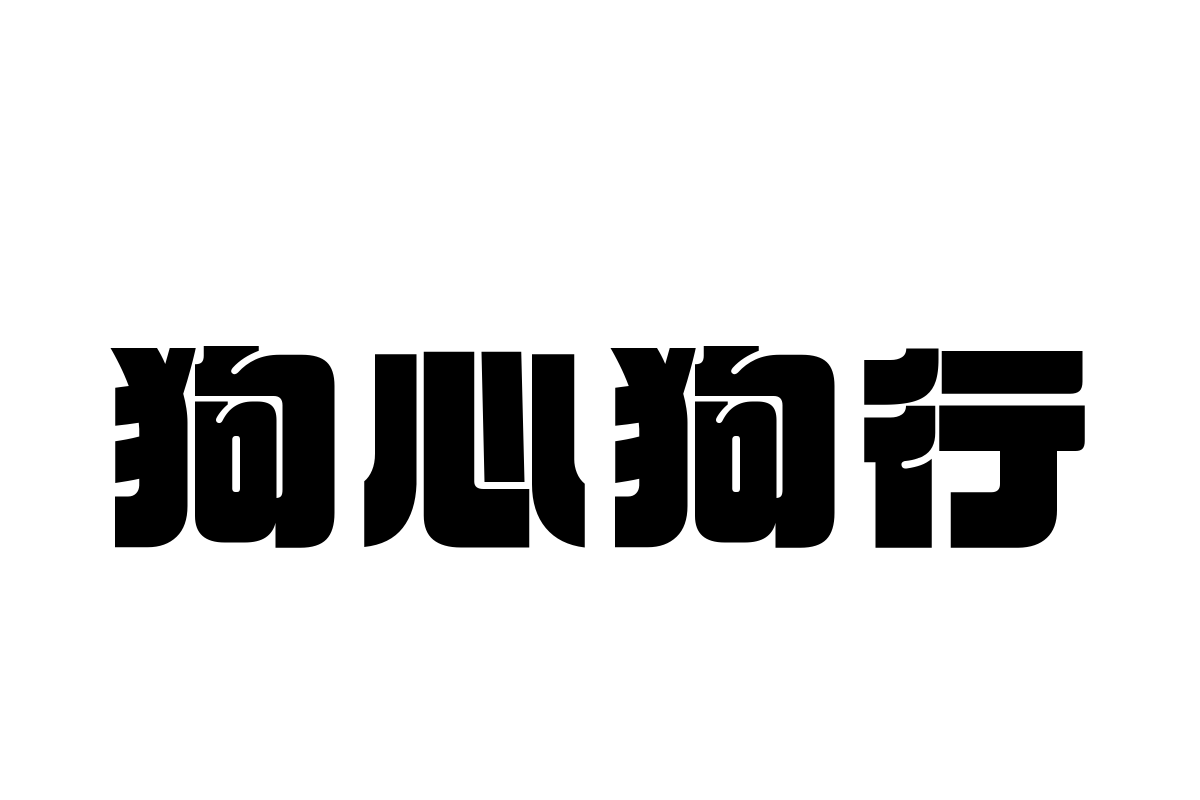
汉仪迪斯科是一款具有现代感的中文字体,适用于各种商业和设计项目。它具有独特的设计和风格,适合用于广告、标志、包装和其他需要引人注目的设计元素。
该字体的特点包括:
– 简洁而优雅的线条,给人一种时尚和现代的感觉。
– 易于阅读和识别,适合用于各种文本内容。
– 支持多种语言,包括简体中文和繁体中文。
总之,汉仪迪斯科是一款功能强大且易于使用的字体,适合各种设计需求。